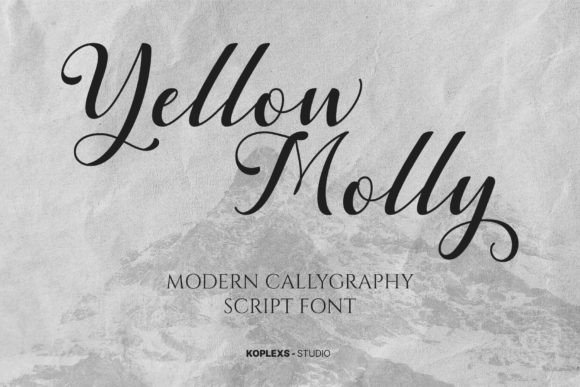
Yellow Molly
Yellow Molly와 같은 κ³ ν’ˆμ§ˆ μžμ‚°μ„ μ°Ύκ³  μžˆλ‹€λ©΄ 이 프리미엄 νŒ¨ν‚€μ§€λŠ” 창의적인 ν”„λ‘œμ νŠΈλ₯Ό μœ„ν•œ ν™˜μƒμ μΈ μ„ νƒμž…λ‹ˆλ‹€.
POD(μ£Όλ¬Έν˜• 인쇄) μ œν’ˆ, κ²°ν˜Όμ‹ μ΄ˆλŒ€μž₯ λ˜λŠ” μ†Œμ…œ λ―Έλ””μ–΄ κ·Έλž˜ν”½μ„ λ§Œλ“€ λ•Œ Yellow MollyλŠ” 이상적인 μ„ νƒμž…λ‹ˆλ‹€.